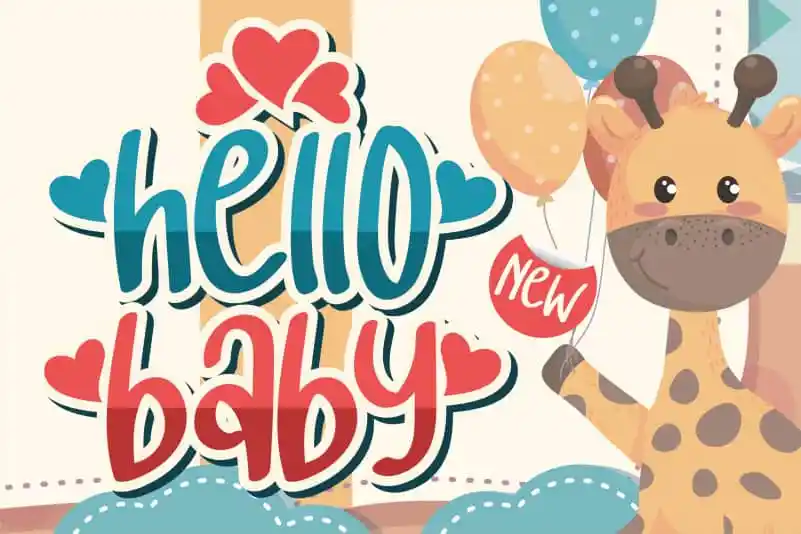
A fonte ‘Hello Baby Display Font’ é uma opção perfeita para aqueles que desejam adicionar um toque divertido a qualquer projeto educacional ou infantil. Embora seja uma fonte de exibição, sua natureza encantadora e cheia de vida torna-a ideal para atividades infantis e trabalhos escolares onde você deseja transmitir uma mensagem leve e inofensiva. Com um toque encantador que pode lembrar alegrias da infância, este fonte tem seu próprio jeito único. Perfecto para aniversários de bebês ou até mesmo projetos relacionados à vida infantil. A cada letra da fonte, você se sente levado para uma fantasia onde o adultério e a pureza coexistem em harmonia perfeita. Esta é a fonte exibicional ideal para qualquer projeto que deseja transmitir um sentimento de encanto e autenticidade aos seus espectadores.